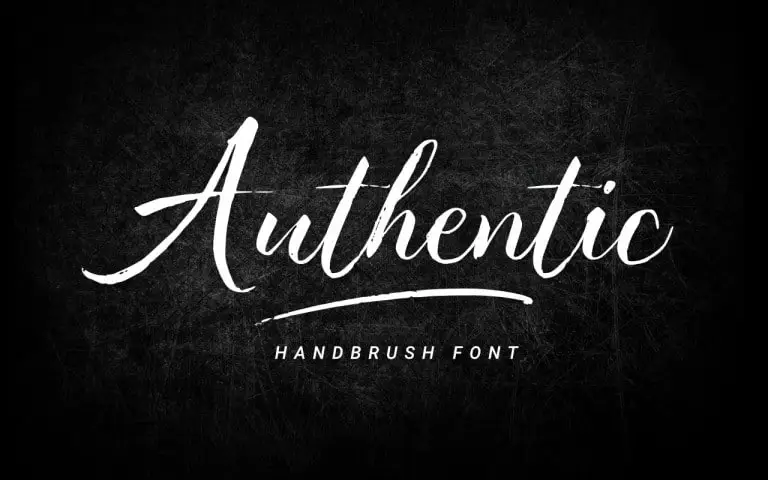
Authentic Brush Font – Fonte Grátis
Authentic Brush Font
A Authentic Brush Font é uma elegante fóntica feita especialmente para quem valoriza a arte manual. Cria-se usando uma pena de pincel, resultando num estilo fluido e sofisticado que se adequa perfeitamente à categoria dos Fonts Script. Esta fonte é ideal para diversas aplicações, como branding, selos, camisetas personalizadas, convites de casamento, produtos de arte manual e muito mais. Com a Authentic Brush Font, você pode escolher um estilo único e distintivo que se encaixa perfeitamente em qualquer projeto gráfico criativo.